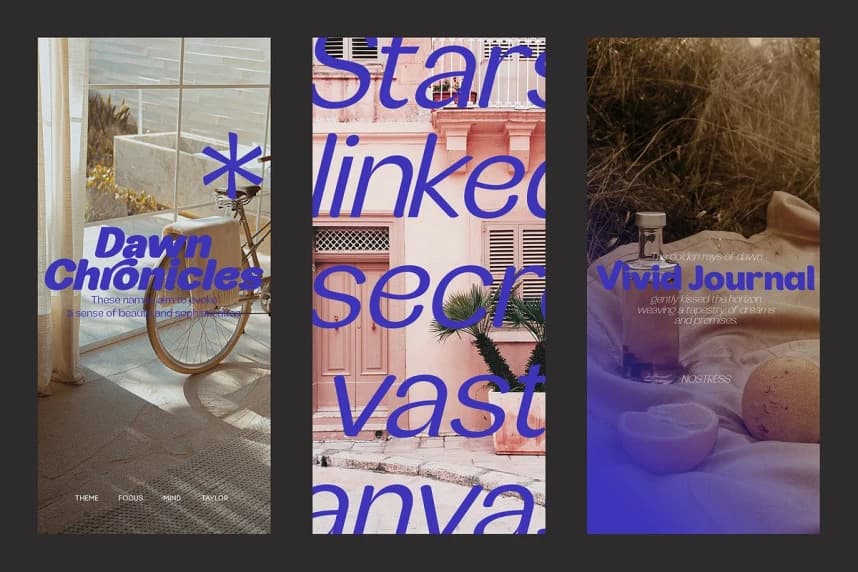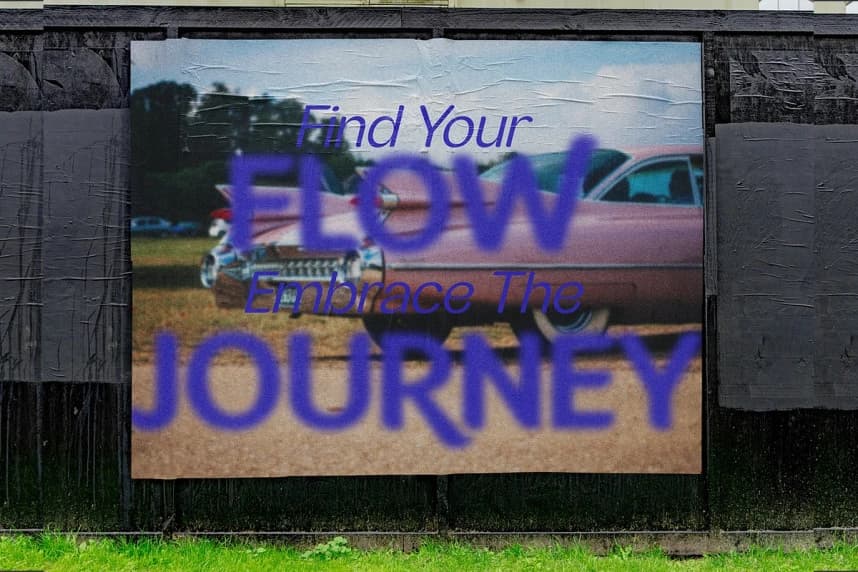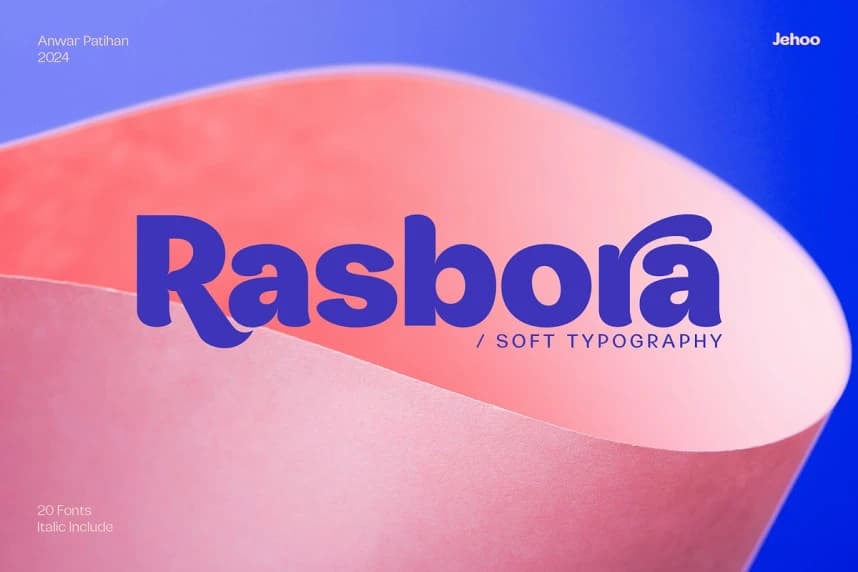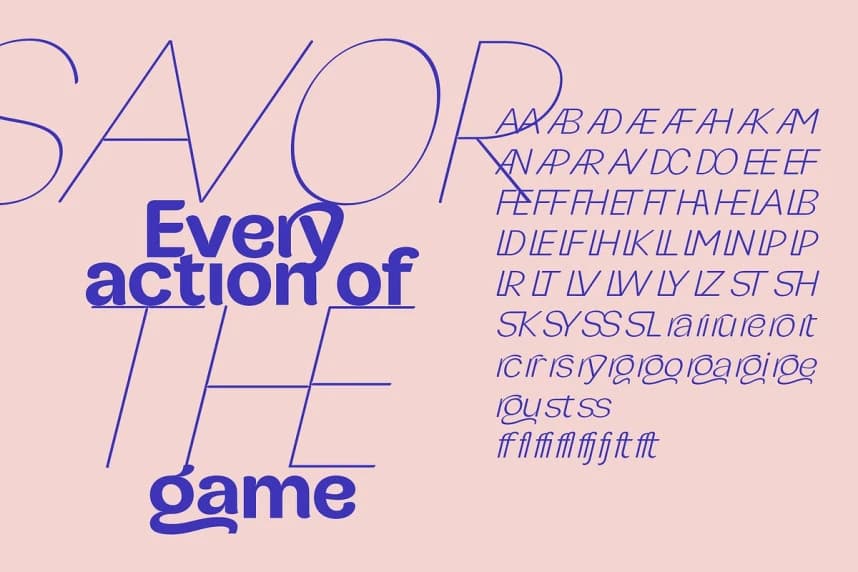
JHC Rasbora Font
JHC Rasbora Font, zarif bir şekilde tasarlanmış bir yazı tipidir ve yumuşak ve rahat bir karakter yansıtır. Bu font, harf biçimlerinde benzersiz bir his veren bir eğriye sahiptir; bu sayede ona nazik, akıcı bir nitelik kazandırır ve hem davetkâr hem de çok yönlüdür.
JHC Rasbora Font, özenle tasarlanmış bir yazı tipidir ve yumuşak ve rahat bir karakter yansıtır. Bu yazı tipinin harf biçimlerinde benzersiz bir eğri hissi bulunur; bu da ona nazik, akıcı bir nitelik kazandırır ve hem davetkâr hem de çok yönlüdür.
JHC Rasbora